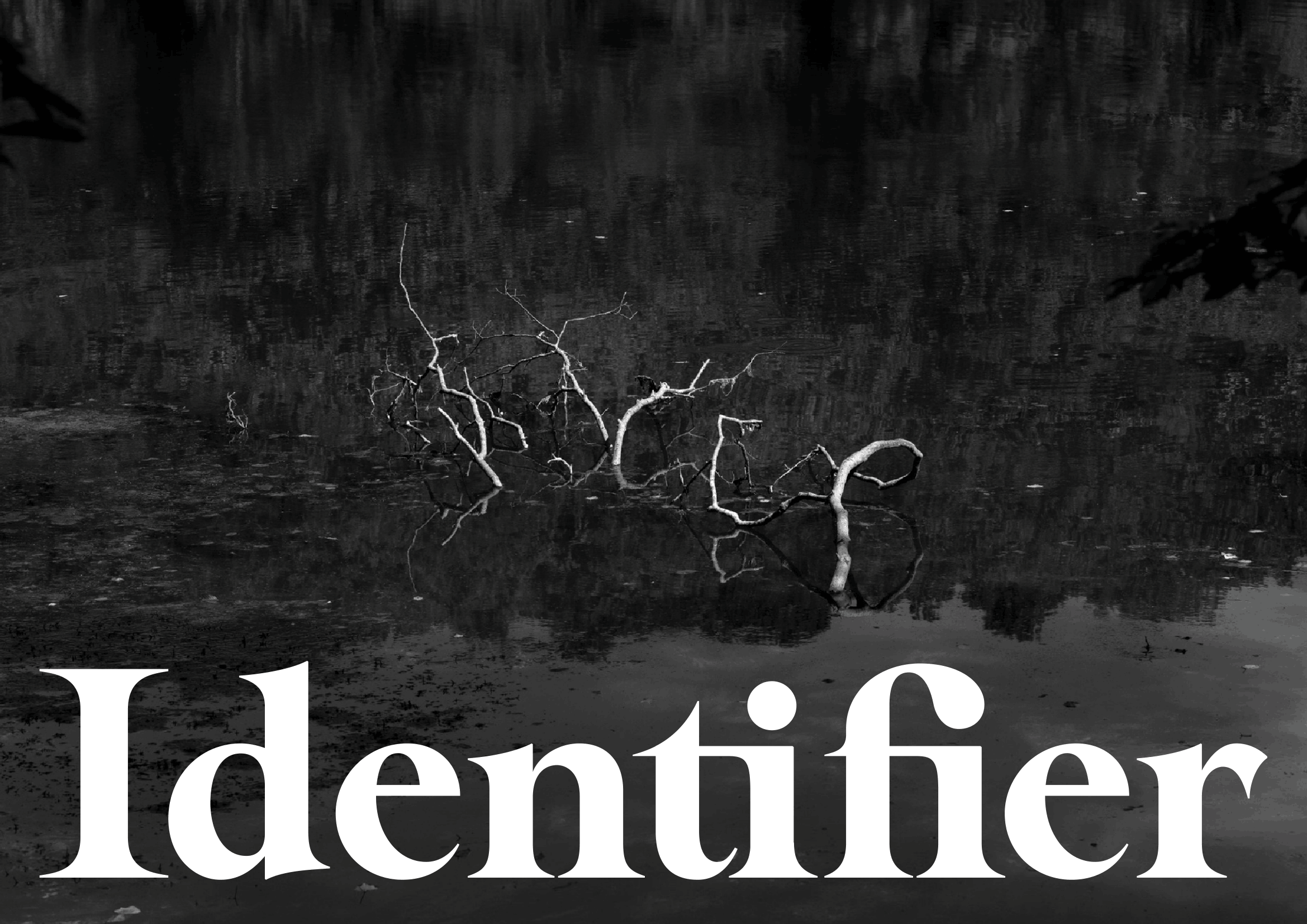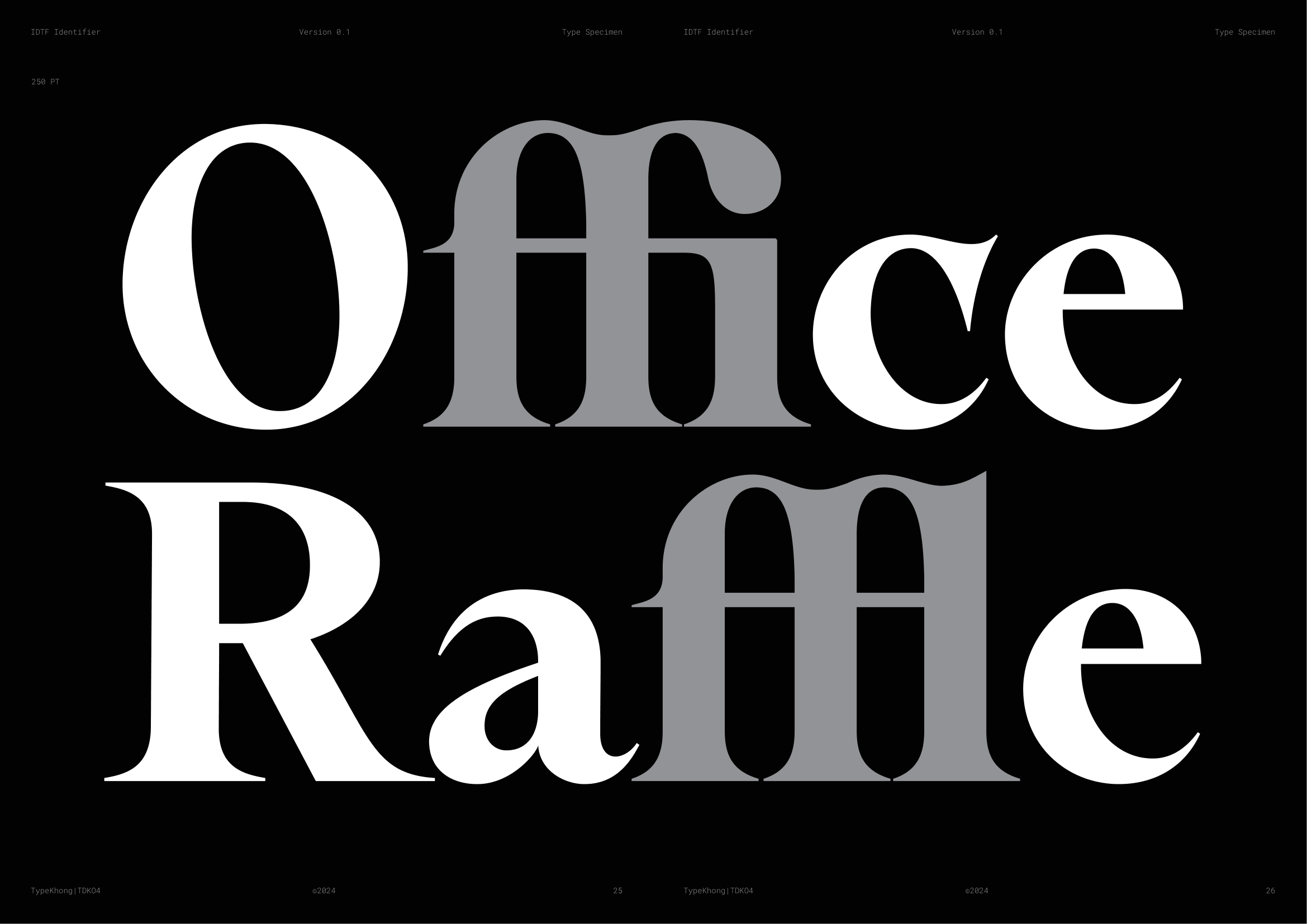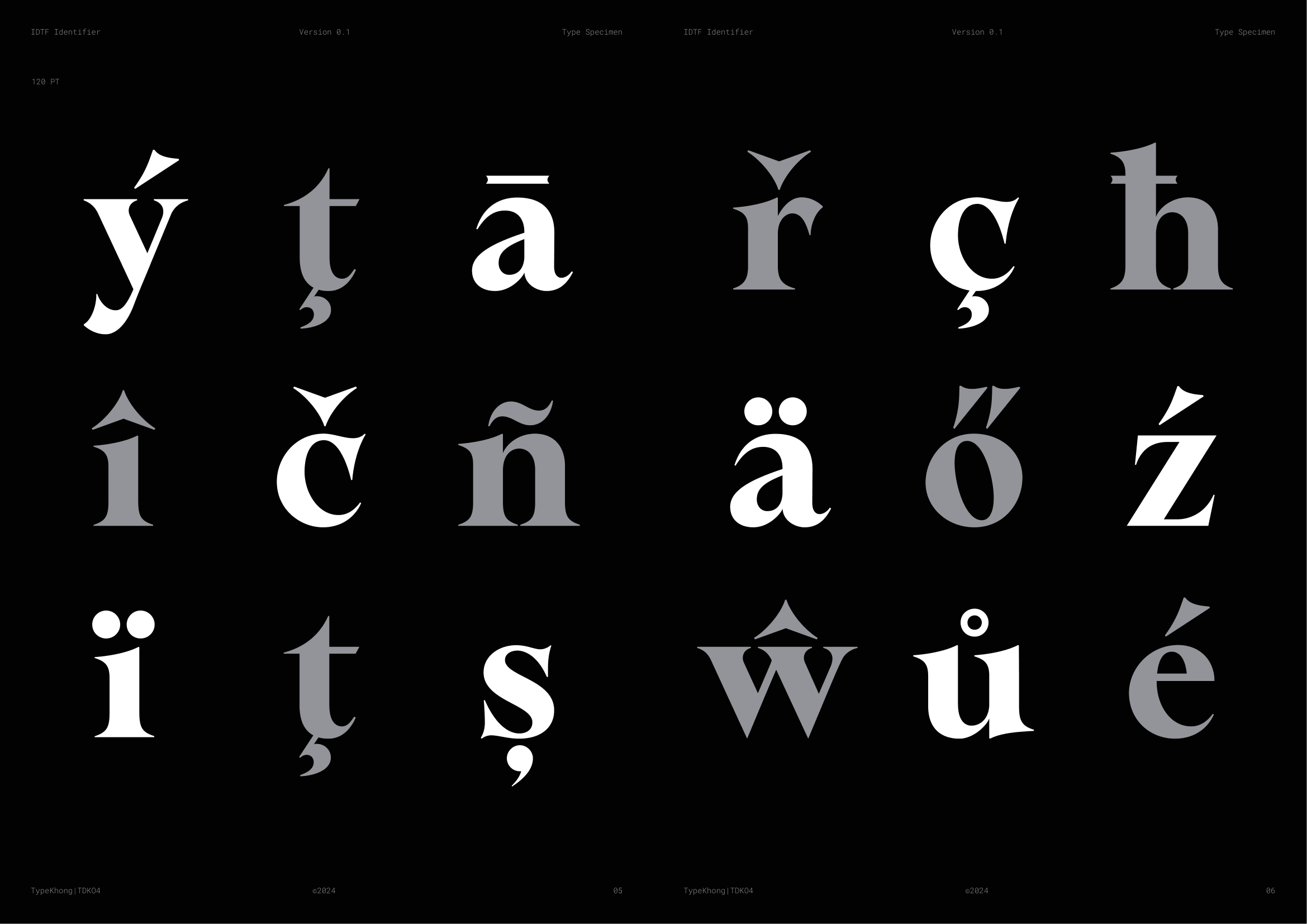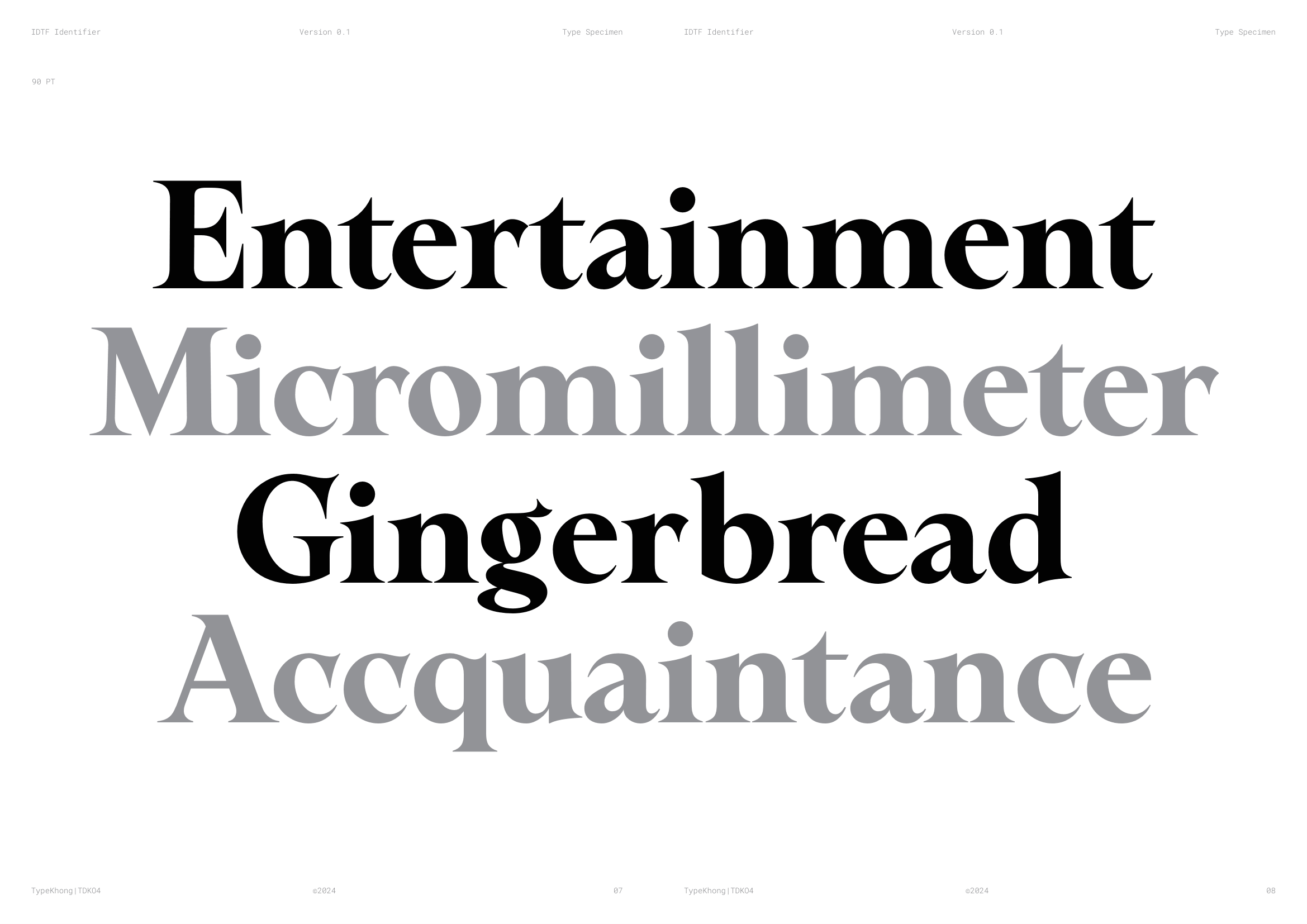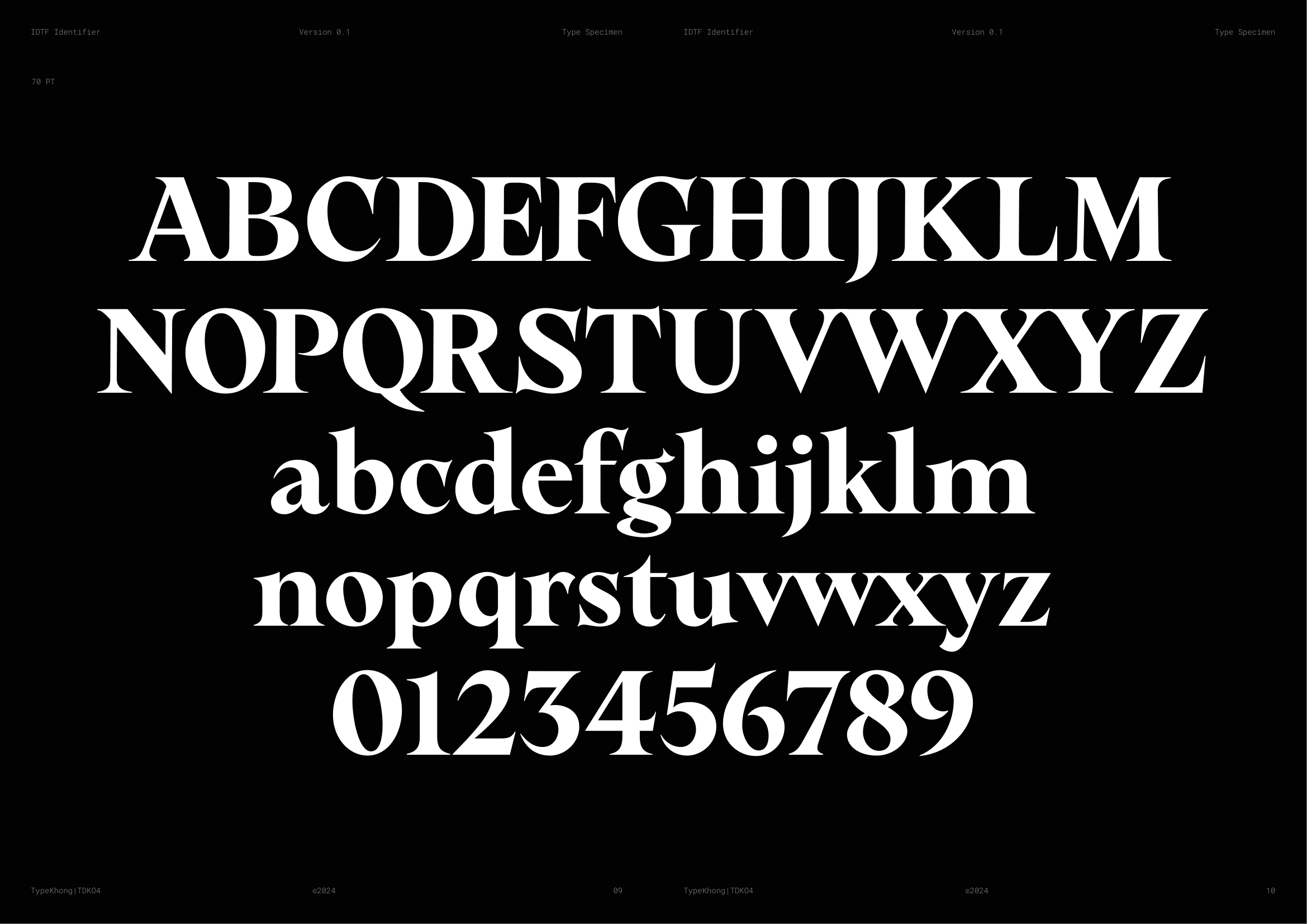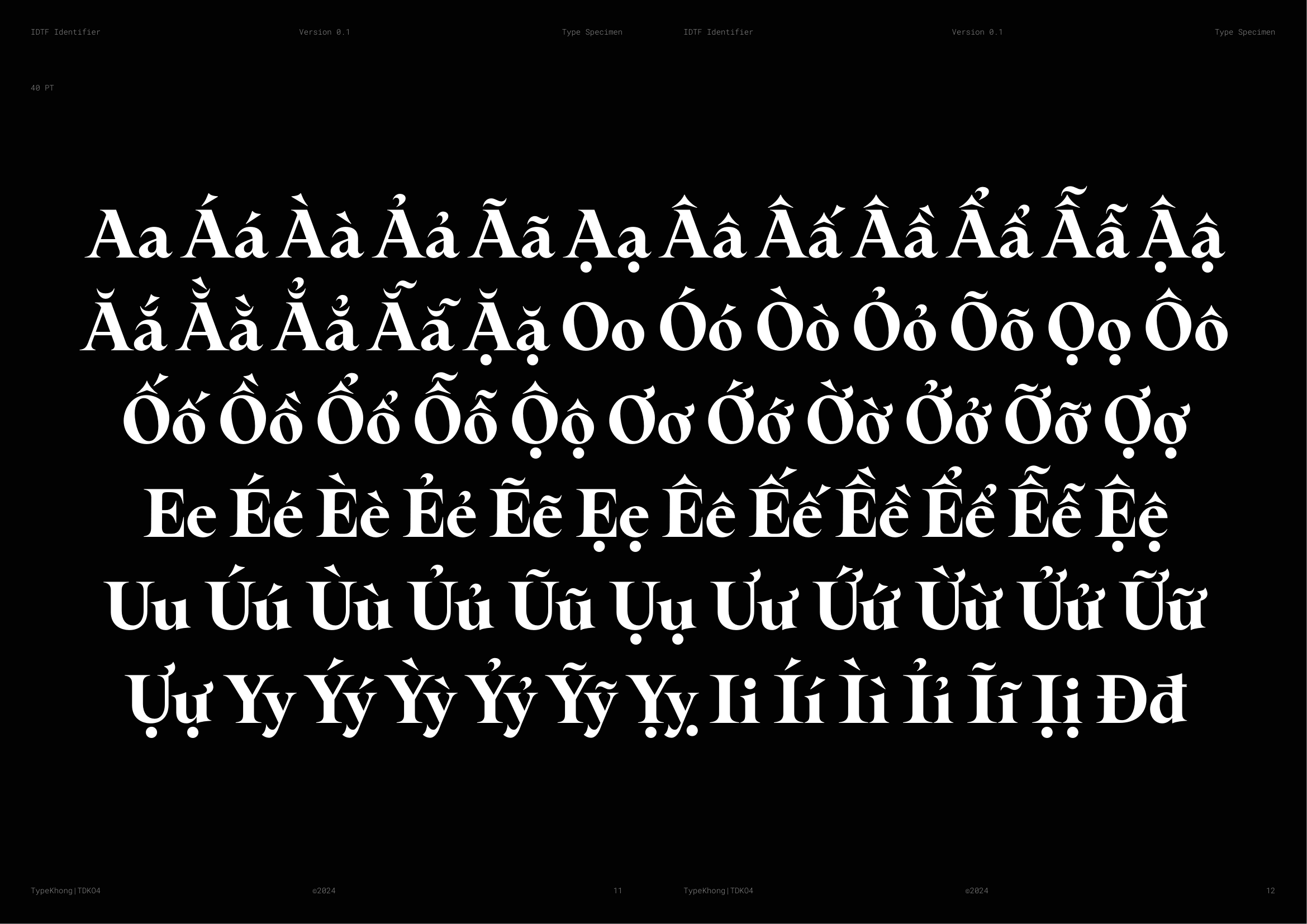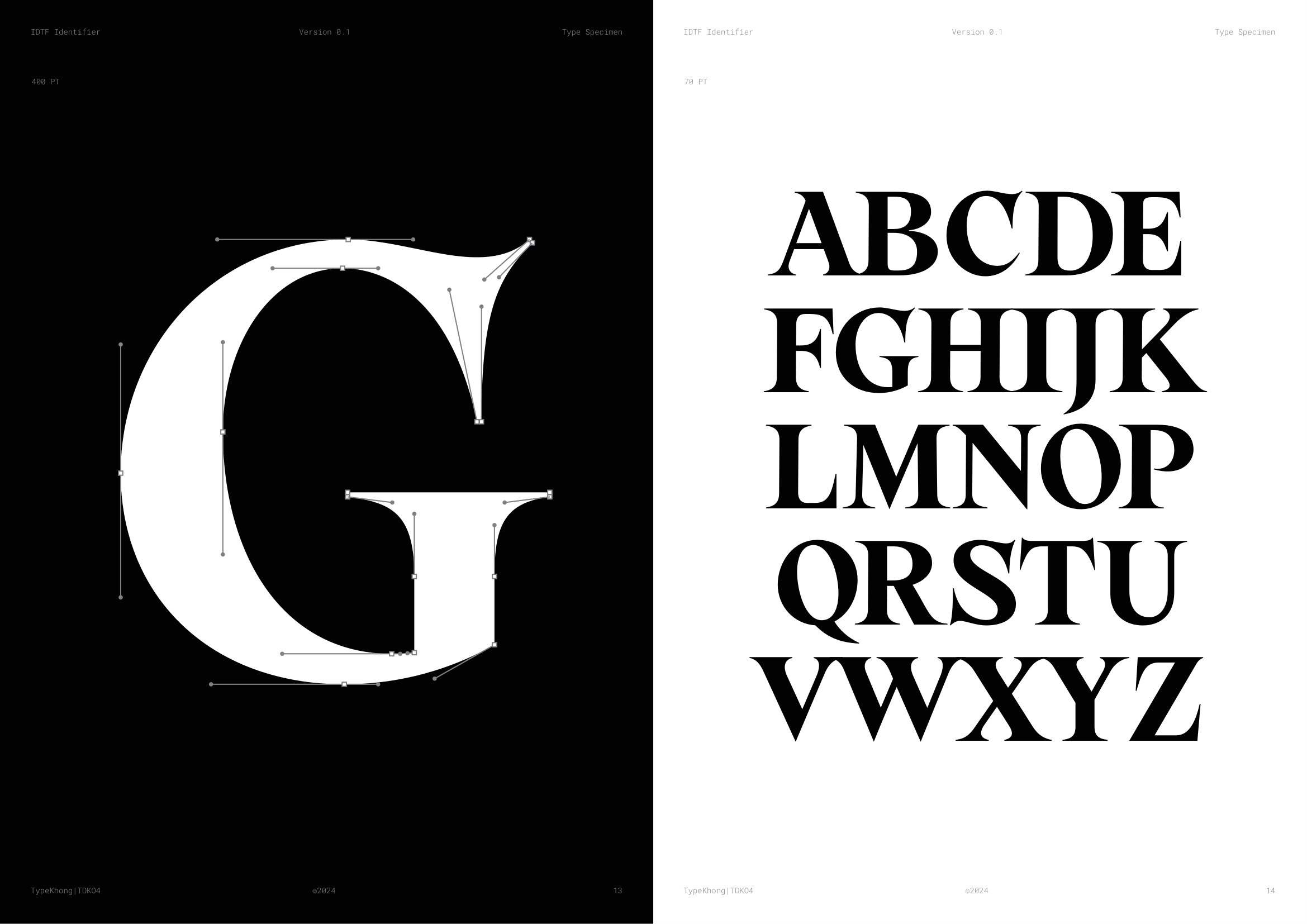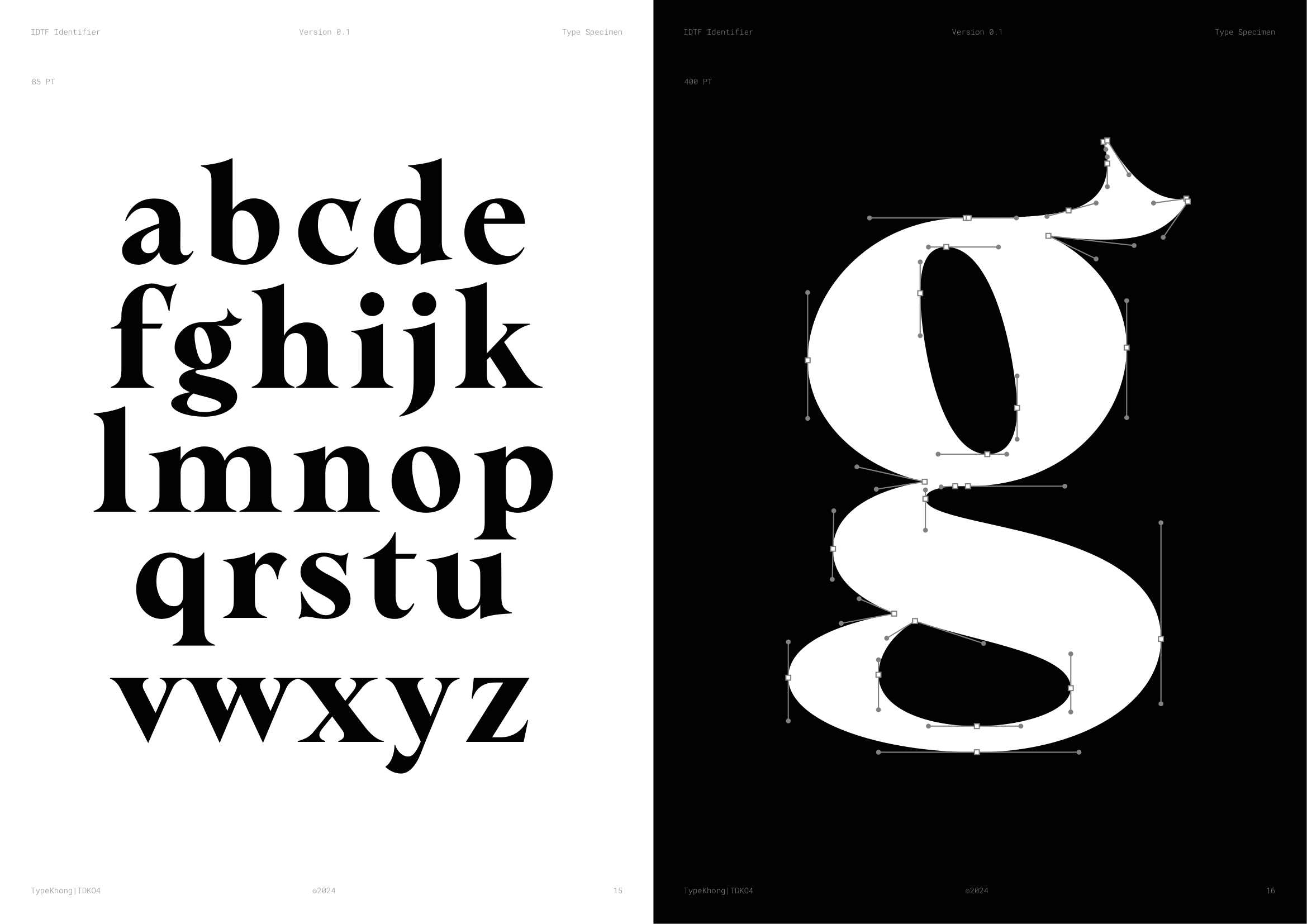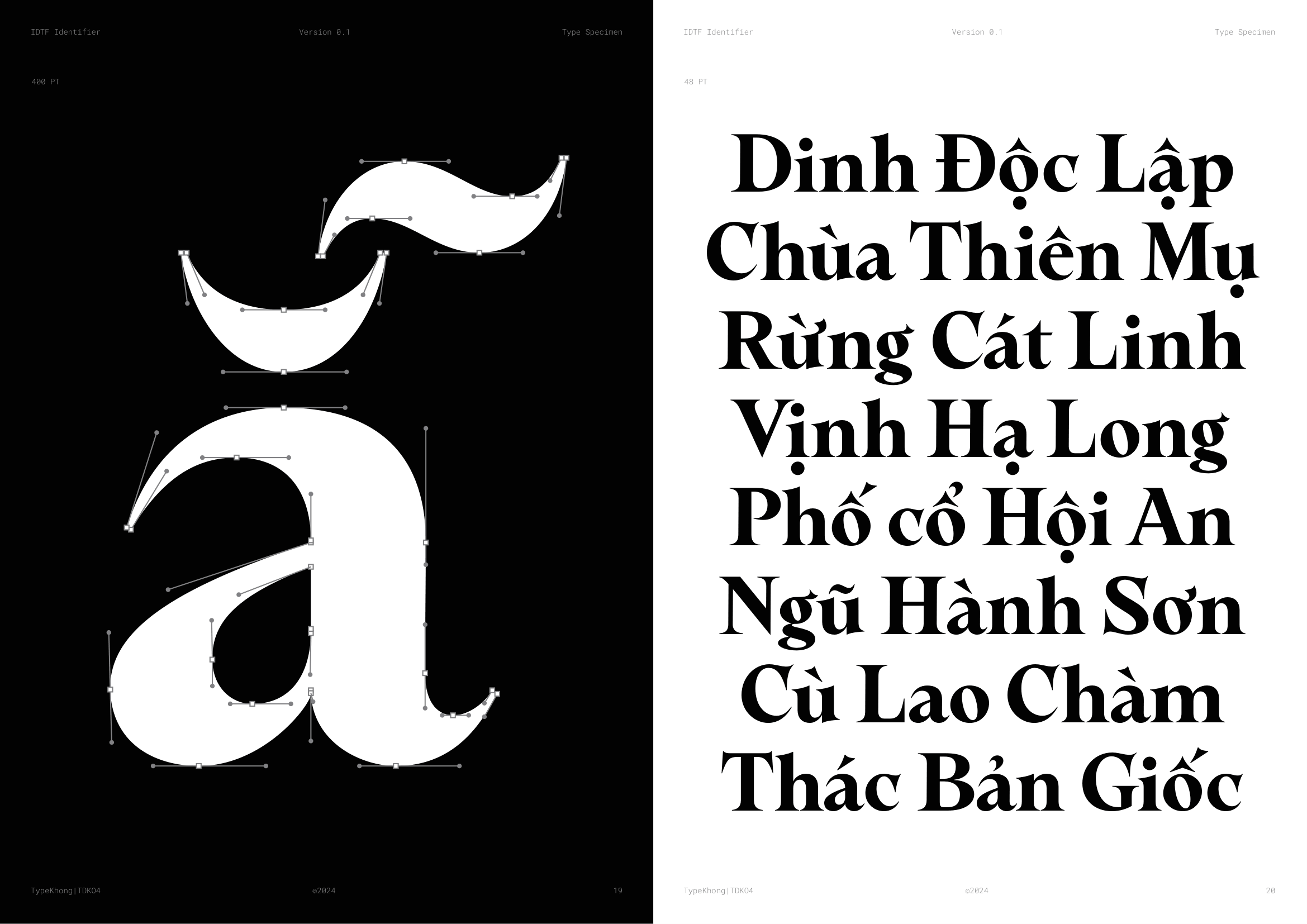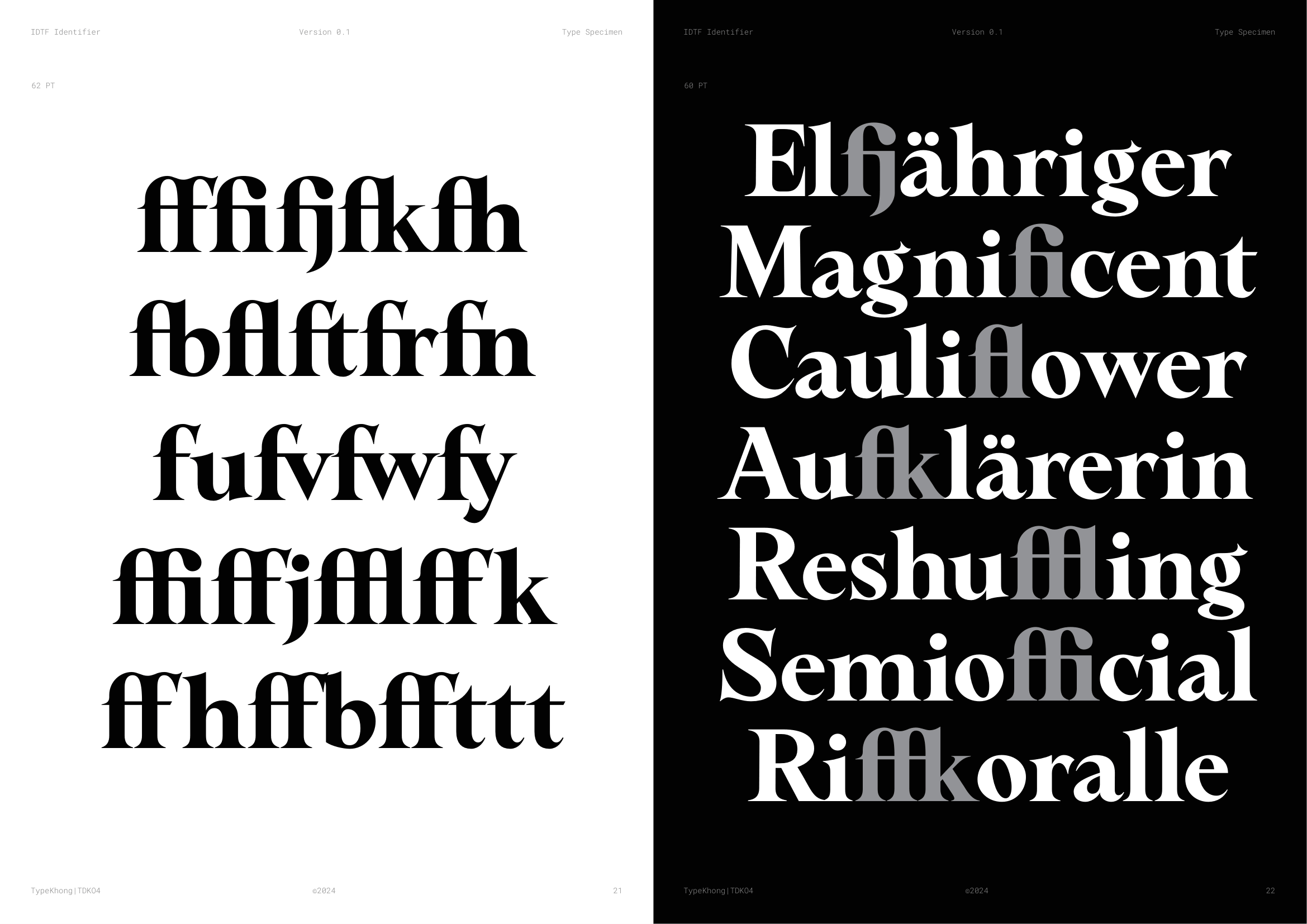
PKT Identifier
Về PKT Identifier: Identifier là một kiểu chữ phục dựng từ Laureate Bold, dòng transitional serif với dáng serif như ống loe. Laureate được khắc lần đầu bởi Keystone Type Foundry tại Philadelphia, PA, vào đầu những năm 1900, dùng cho các tiêu đề khổ lớn. Lấy cảm hứng từ những tiêu đề serif đậm, chặt chẽ của thời đại phóng khoáng ấy, Identifier ra đời với mục đích phục dựng bộ chữ, tinh chỉnh các nét, khắc phục những điểm yếu của font cũ. Sau đó bổ sung đầy đủ bộ dấu tiếng Việt theo cách sắc nét và nổi bật hơn.
Transitional Serif
Display
Phan Kim Thoại